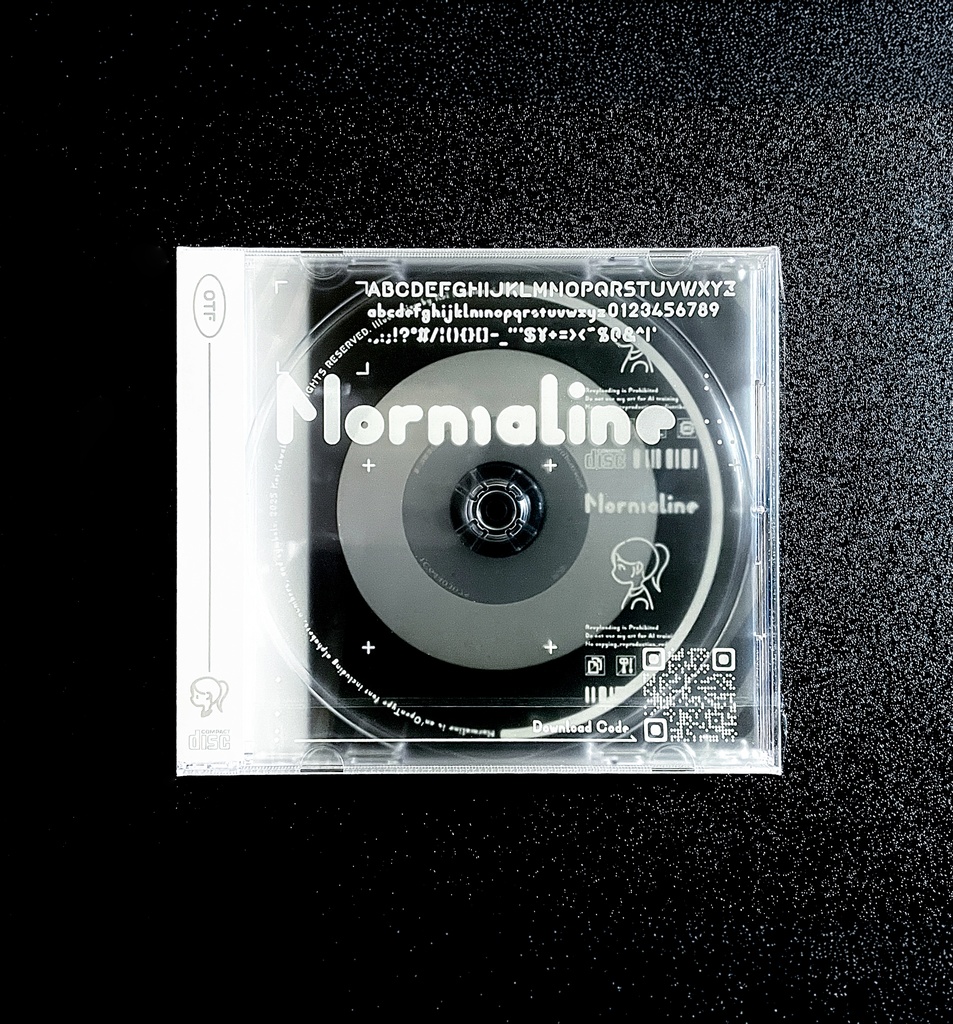
COMITIA156Kei Kawakami online storeオリジナルフォント”Normaline”CD-ROMShips within 15 daysOut of StockPhysical (direct)2,200 JPYRequest Restock Notice MailUnrequest Restock Notice MailAbout Giftオリジナルフォントのデータが入ったCD-ROMです。 英数字・記号のみのミニマルなフォントです。 (商用利用可) CDを読み込むかパッケージのQRから入れるページからダウンロードしてお使い頂けます。パスワードはパッケージ裏面に記載しております。 詳細は同梱の使用許諾契約書をご確認ください。Kei Kawakami online storeVisit FANBOX!COMITIA156StickersOut of Stock水族館チケット風ステッカー(海水)Kei Kawakami online store550 JPYCOMITIA156Acrylic KeychainsOut of Stockアクリル製アンブレラマーカーKei Kawakami online store1,050 JPYCOMITIA156Keychains & Charms & StrapsOut of Stock豆本キーホルダー+ミニステッカーシートKei Kawakami online store1,200 JPYCOMITIA156Acrylic FigureOut of Stock箱付きアクリルクリップKei Kawakami online store1,100 JPYCOMITIA156StickersOut of Stockブリスター風ステッカーセットKei Kawakami online store550 JPYCOMITIA156StickersOut of Stock水族館チケット風ステッカー(淡水)Kei Kawakami online store550 JPYDESIGN FESTA vol.62Laminated CardsOut of StockレンチキュラーカードKei Kawakami online store550 JPYCOMITIA156Illustration & CG collectionsOut of StockMINI ARTBOOKKei Kawakami online store1,200 JPYTote bagsOut of Stock缶バッヂ付きトートバッグ(hato)Kei Kawakami online store2,700 JPYTote bagsOut of Stock缶バッヂ付きトートバッグ(penguin)Kei Kawakami online store2,700 JPYCOMITIA156Illustration & CG collectionsOut of StockアートブックVol.2 PLANTKei Kawakami online store1,800 JPYCOMITIA156Illustration & CG collectionsOut of StockアートブックVol.1 FLOATKei Kawakami online store1,800 JPYDESIGN FESTA vol.62CalendarsOut of Stock【SALE】卓上カレンダー 2026Kei Kawakami online store750 JPYSee More